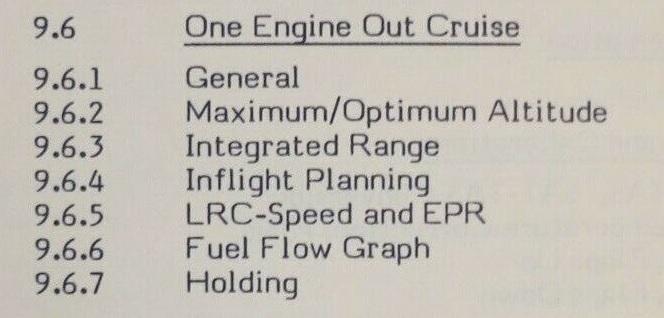
Suche einer Schrift (Lufthansa Handbuch)
ich bin auf der Suche nach einer Schrift in welcher bei der Lufthansa in den 70iger bis 80iger Jahren interne Druckerzeugnisse gedruckt wurden. Soweit ich mich erinnern kann, wurden die Vorlagen in der Regel bei den Abteilungen erstellt und dann nach Köln in die Hausdruckerei geschickt. Was nun dort gemacht wurde, offset-druck oder richtig klassisch gesetzt, daß weiß ich nicht. Bei dem Angehängten Bild handelt es sich um einen Ausschnitt aus so einem Handbuch.
Die Schrift im Beispiel läuft nicht dicktengleich (siehe i und m). Das spricht gegen eine klassische Schreibmaschinenschrift, deren Buchstabenbreiten nicht proportional sind.
Gab es nicht bei Kugelkopf- und Typenraddruckern die Möglichkeit, proportional zu drucken?
Schon verstanden. Eine "klassische" Schreibmaschinenschrift ist das eh nicht, die wär einem sonst schon mal untergekommen. Die Formen sind schon sehr speziell. Bisher ist’s ja nur eine Vermutung von mir, dass es eine Schreibmaschinenschrift sein müsste.
erst mal vielen herzlichen Dank für die Antworten, besonders aus dem ersten Post. Ich bin mir mittlerweile sicher das die Vorlagen mit einer Schreibmaschine erstellt wurden. Unter
gibt es eine Schrift mit dem Namen "Report" die könnte es sein, besonders weil, zumindest in einigen Abteilungen in Frankfurt, damals viel mit IBM Schreibmaschinen gearbeitet wurde.
Die Großbuchstaben der Report sind aber deutlich anders.
Aber IBM konnte wohl schon 1947 Proportionalschriften auf Schreibmaschinen realisieren.